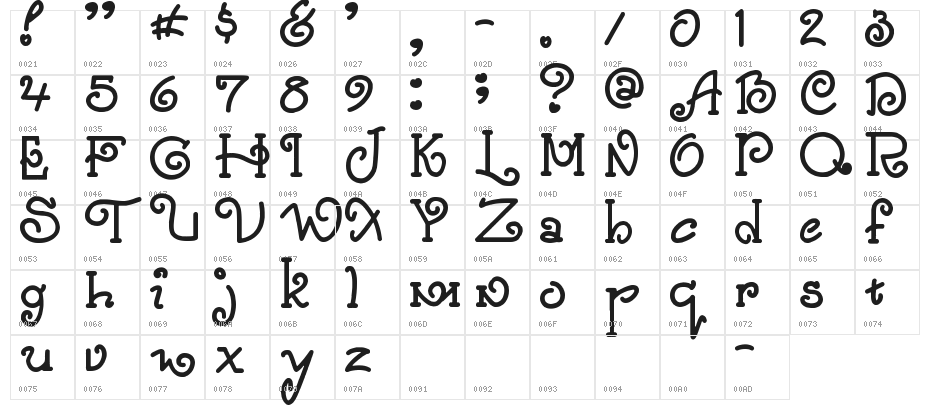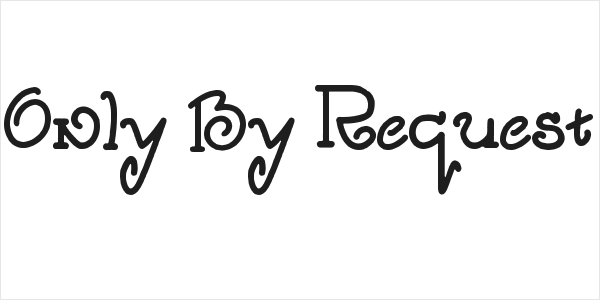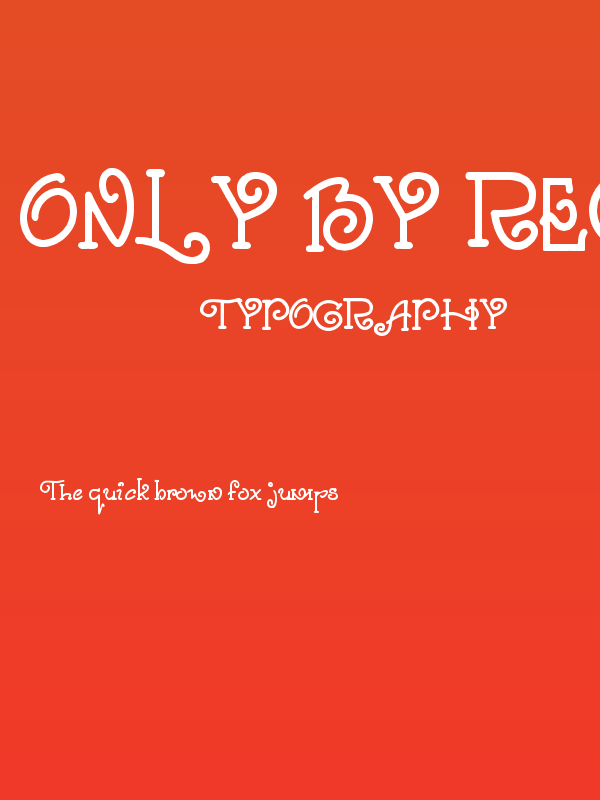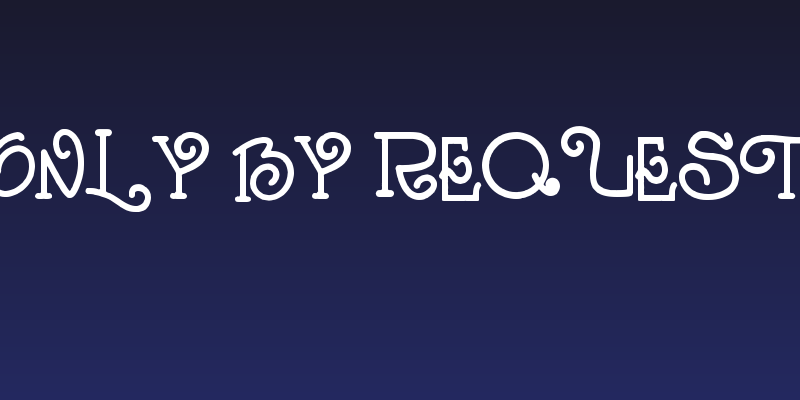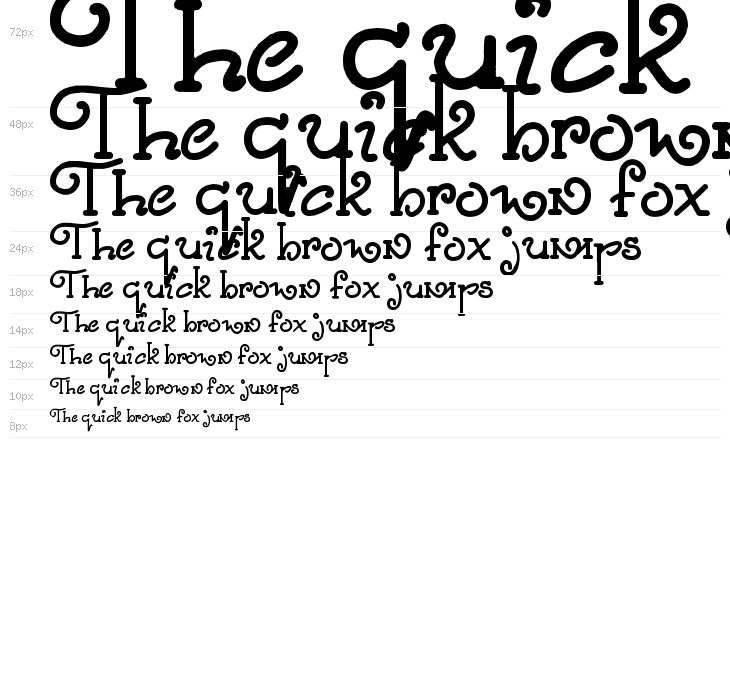
Only By Request Font
✎ Decorative
| 分类 | Decorative |
| 整体风格 | Playful and Artistic |
| 使用场景 | Headlines, Logos, Creative Projects |
| 推荐项目 | Ideal for children's books, playful branding, greeting cards, and creative posters. |